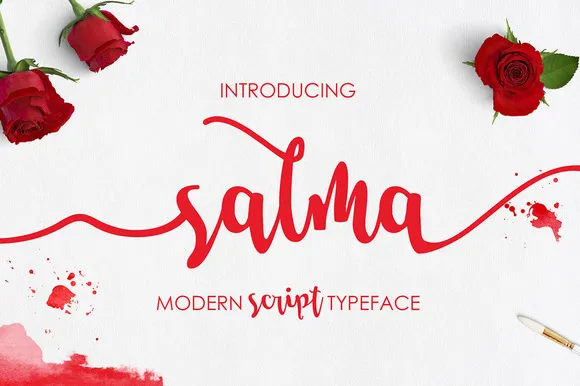
Salma Script Font – Download Grátis
A Salma Script Font é uma elegante solução para designers que valorizam estilos únicos e modernos. Desenvolvida pelo designer MissinkLab Studio, essa fonte premium está disponível gratuitamente hoje no Creativemarket. Com sua arte manual de caligrafia e estilo fresco e contemporâneo, a Salma Script proporciona um look fluido e natural, ideal para impressões digitais que imitam escrita real. Essencialmente versátil, ela é perfeita tanto para projetos digitais como físicos, desde letras de logotipos até t-shirts personalizadas. Seja você um designer digital criando letras aprimoradas, um artista gráfico trabalhando em uma camiseta customizada ou mesmo aquele que está buscando um elemento único para embalagens de produtos, a Salma Script será o seu fonte ideal.